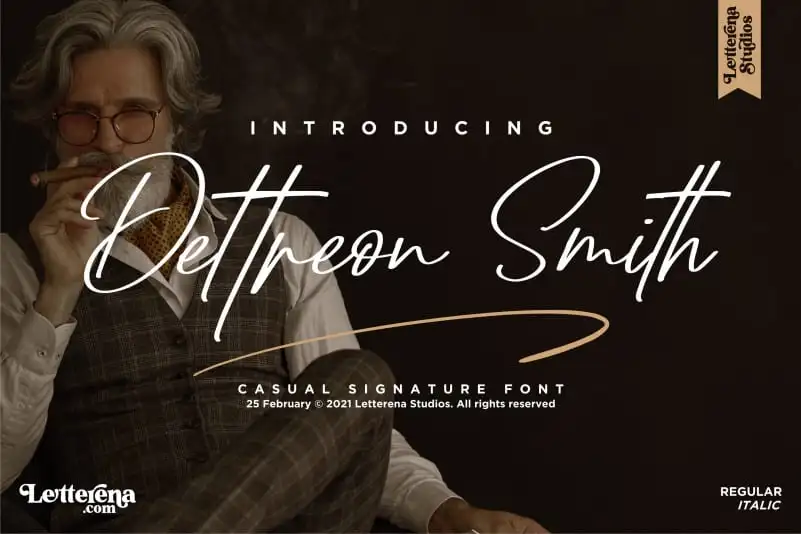
Dettreon Smith Font – Download Grátis
A fonte ‘Dettreon Smith Font’, criada pelo designer letterenastudios, é uma elegante escolha para projetos que exigem um toque personalizado e sofisticado. Este script font é perfeito tanto para trabalhos de marca como identidade visual, quanto para design de móveis de casa, embalagens de produtos, itens do dia a dia, design gráfico ou até mesmo capas de livros. Seu charme elegante se encaixa perfeitamente em qualquer projeto que exige um toque de letra autêntica e sofisticada. Dessa forma, ‘Dettreon Smith Font’ é uma opção ótima para aqueles buscando um design com a personalidade única necessária para o seu próximo projeto de design. Engane-se se pensar que este é apenas mais um script font – ele carrega consigo nuances e detalhes únicos que o tornam um diferencial em qualquer obra de arte visual.